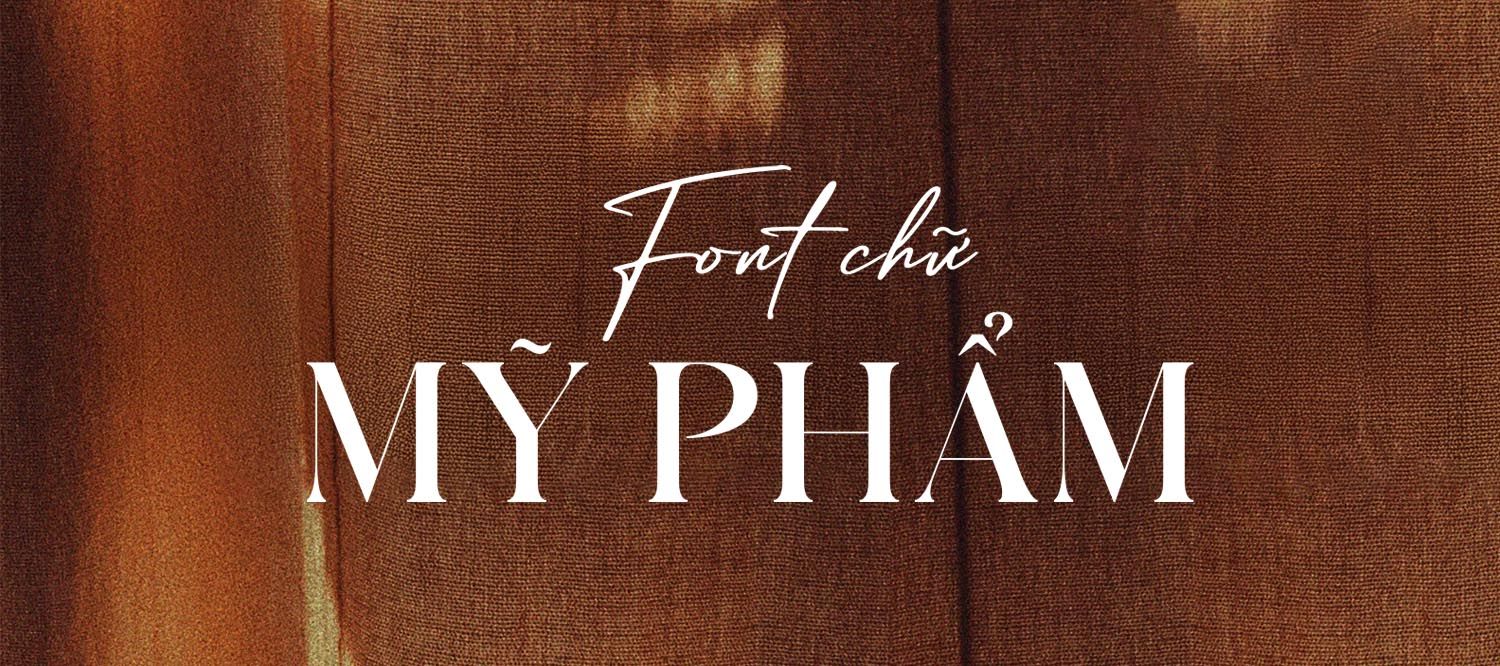
![[Tải Xuống] Tổng Hợp 15+ Font Chữ Mỹ Phẩm Đẹp Cho 2025](https://cdn.s99.vn//cloud/Bt0lgA_font-chu-my-pham-viet-hoa-depjpg.jpeg)
Trong ngành mỹ phẩm, font chữ không chỉ đơn thuần là kiểu chữ để hiển thị thông tin mà còn đóng vai trò là “gương mặt” của thương hiệu. Font chữ mỹ phẩm được hiểu là những kiểu chữ được thiết kế hoặc lựa chọn chuyên biệt để phù hợp với lĩnh vực làm đẹp – thường mang hơi hướng sang trọng, mềm mại và tinh tế. Việc chọn đúng font chữ giúp thương hiệu mỹ phẩm khẳng định phong cách, tạo sự chuyên nghiệp và gây ấn tượng mạnh mẽ với khách hàng ngay từ cái nhìn đầu tiên.
NVN Motherland Signature mang phong cách chữ ký mềm mại, tinh tế với những đường nét uyển chuyển. Font này rất phù hợp cho các thương hiệu mỹ phẩm cao cấp, muốn tạo cảm giác sang trọng và cá nhân hóa. Đặc biệt, nó giúp logo hoặc bao bì trở nên độc đáo, dễ ghi nhớ.
TH Renddonika là font viết tay lãng mạn, kết hợp hoàn hảo giữa sự mềm mại và nữ tính. Font thích hợp sử dụng cho thương hiệu mỹ phẩm, spa, hoặc các dòng sản phẩm thiên về làm đẹp tự nhiên. Nó mang lại cảm giác gần gũi và tinh tế trong từng thiết kế.
TH Bramostia mang phong cách chữ ký uyển chuyển, có độ dày vừa phải và đường cong mềm mại. Font này thường được dùng cho logo hoặc slogan của thương hiệu mỹ phẩm, tạo ấn tượng chuyên nghiệp nhưng vẫn giữ được nét nữ tính.
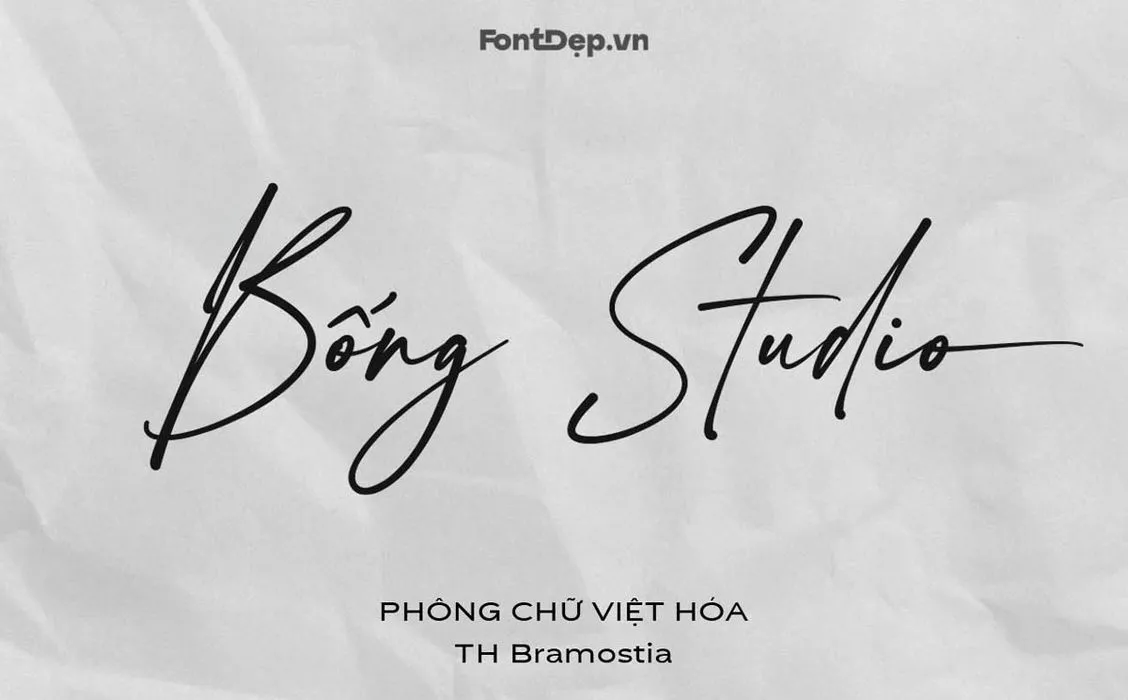
TH Bengoda mang hơi thở hiện đại, nét viết tay cá tính nhưng vẫn tinh tế. Đây là lựa chọn lý tưởng cho các thương hiệu trẻ, năng động trong ngành mỹ phẩm, đặc biệt khi cần thể hiện phong cách cá nhân hóa.
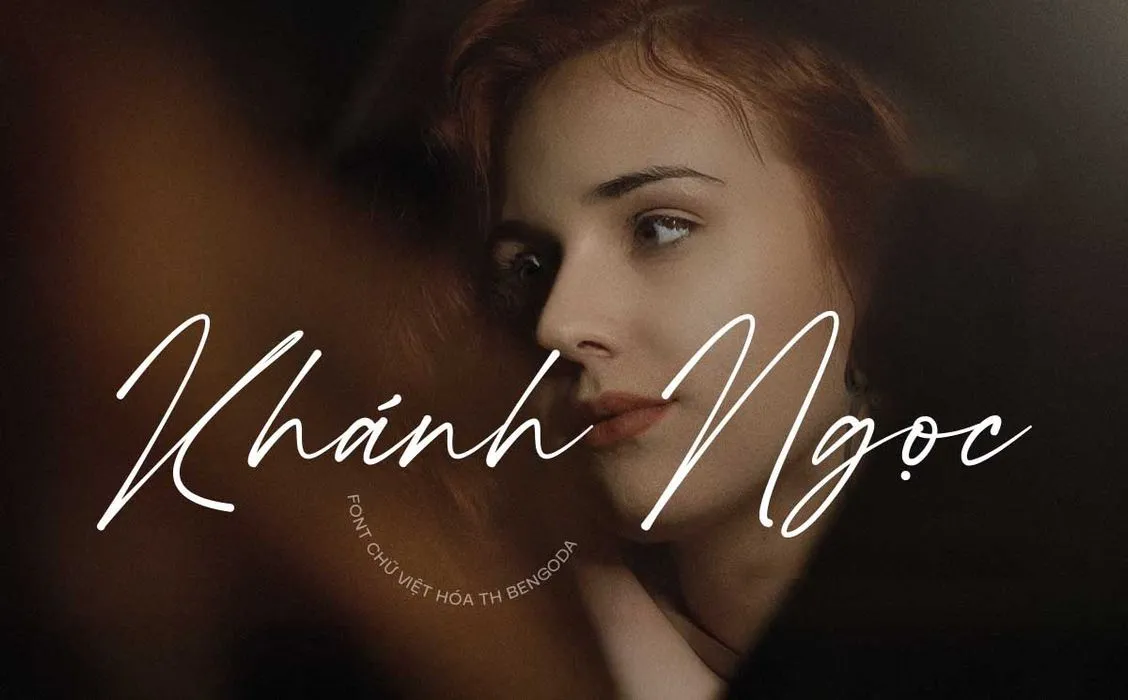
TH Boulderstone là font chữ ký mạnh mẽ, kết hợp giữa sự tinh tế và sự tự tin. Phù hợp cho logo mỹ phẩm muốn thể hiện đẳng cấp, cuốn hút ngay từ ánh nhìn đầu tiên.
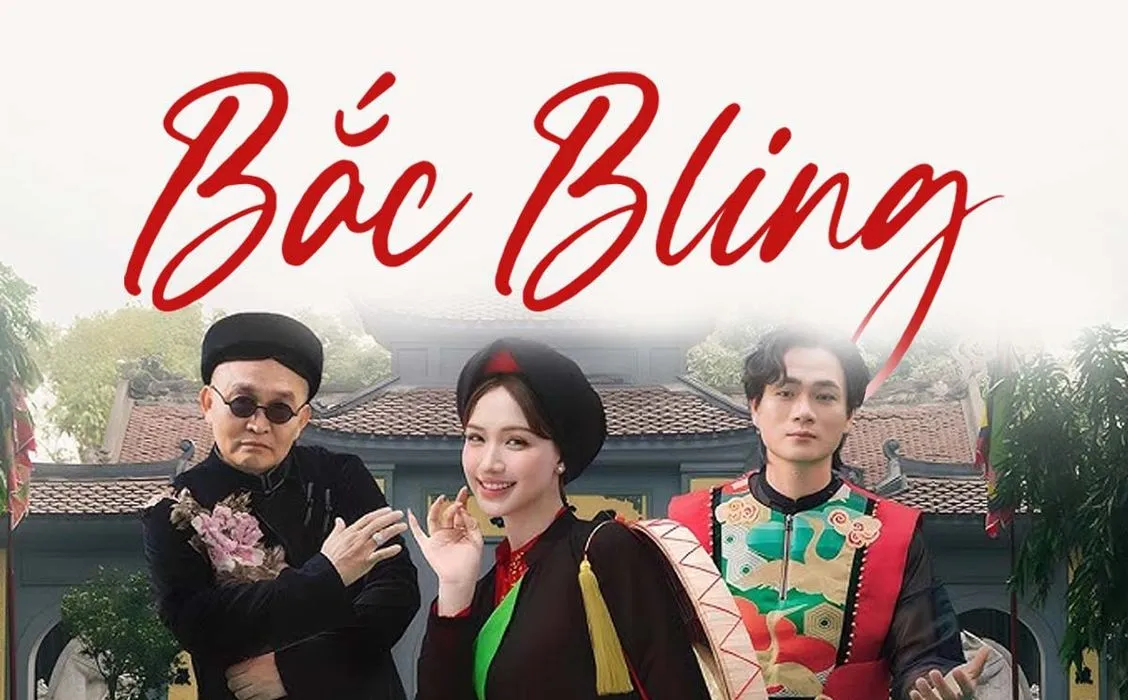
TH Saviera là font sans-serif hiện đại, thanh lịch với đường nét gọn gàng và cân đối. Rất thích hợp cho các thiết kế bao bì, nhãn sản phẩm mỹ phẩm cần sự rõ ràng nhưng không mất đi tính thẩm mỹ.
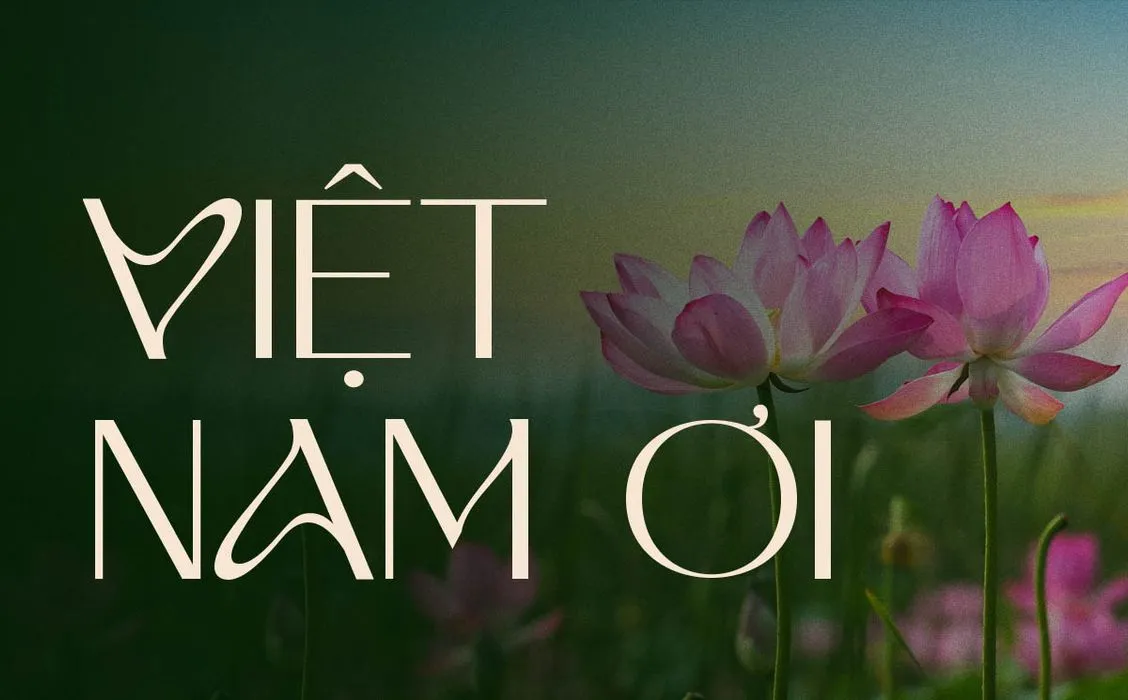
TH Adriana Gabrielle là font chữ viết tay mềm mại, tạo cảm giác sang trọng và tinh tế. Font thường được ứng dụng trong các thiết kế spa và mỹ phẩm thiên về sự thư giãn, nhẹ nhàng.
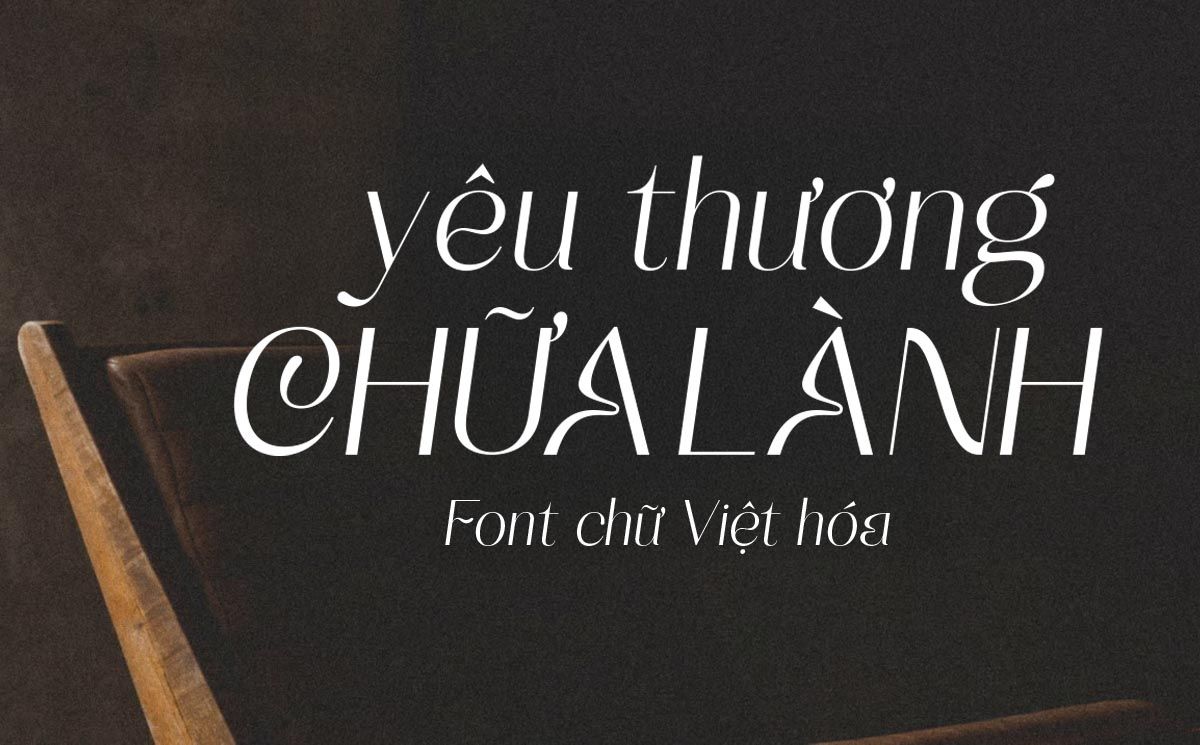
TH Cemains là font sans-serif luxury, mang lại sự hiện đại và sang trọng cho bao bì mỹ phẩm. Font này phù hợp cho các thương hiệu cao cấp, nhấn mạnh sự tinh tế và độ chuyên nghiệp.
TH Grotley mang phong cách sans-serif tinh tế, nhẹ nhàng và hiện đại. Đây là font lý tưởng cho các thiết kế cần sự cân bằng giữa tính thẩm mỹ và tính ứng dụng, đặc biệt là bao bì skincare.
SVN Archattes là một font sans-serif tối giản, miễn phí và dễ dùng. Nhờ sự gọn gàng, font này phù hợp cho các thiết kế website hoặc nhãn mỹ phẩm chú trọng sự rõ ràng và chuyên nghiệp.
TH Luxury là font serif mang phong cách sang trọng, tạo nên dấu ấn cao cấp cho logo hoặc bao bì mỹ phẩm. Nó giúp thương hiệu trở nên chuyên nghiệp và đẳng cấp hơn.
TH Cinema Sunday là font serif thanh lịch, phù hợp cho lĩnh vực làm đẹp và spa. Với các đường nét mềm mại, font này dễ ứng dụng trong poster, tạp chí và bao bì mỹ phẩm.
Tác giả gốc: StringLabs
Việt hóa: TH Team
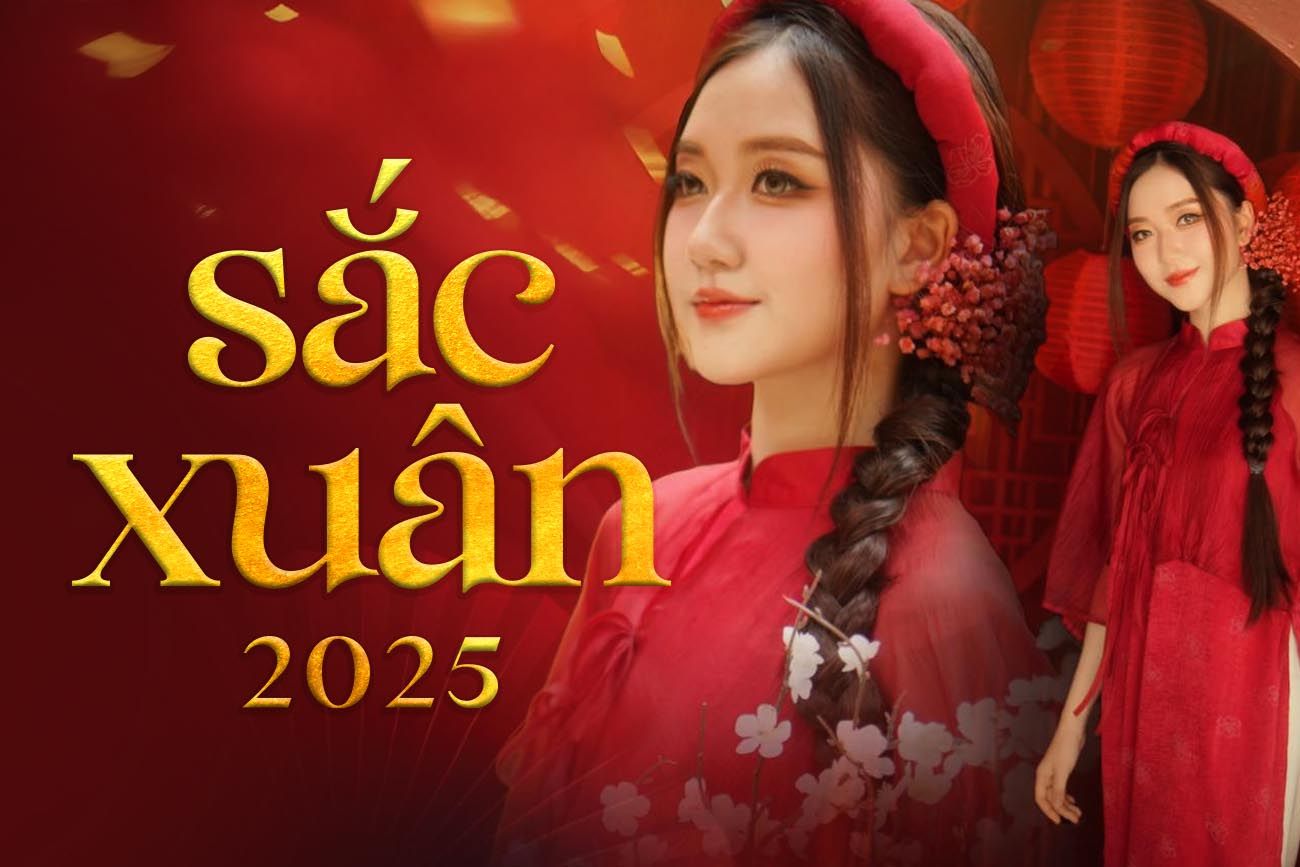
TH Luxury 6 mang phong cách serif hiện đại, sang trọng, được thiết kế để thể hiện sự đẳng cấp. Đây là font lý tưởng cho thương hiệu mỹ phẩm cao cấp, nhấn mạnh sự chuyên nghiệp.
Việt hóa: TH Team
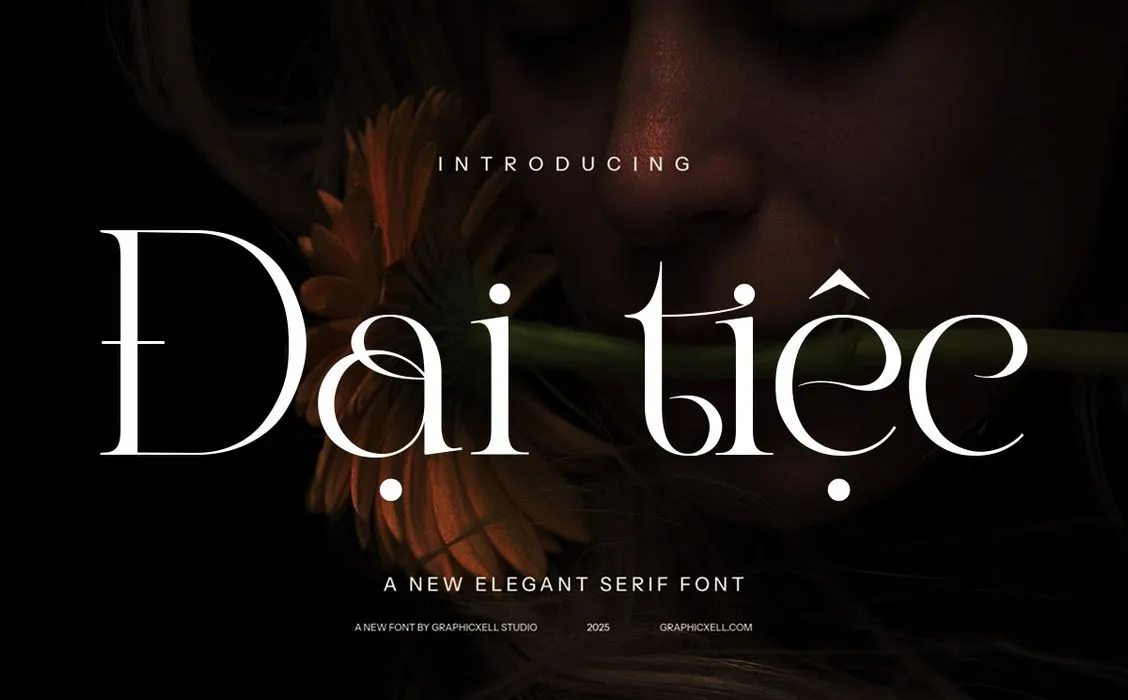
TH Luxury 5 là font serif với các nét mạnh mẽ và rõ ràng, thích hợp cho thương hiệu mỹ phẩm muốn truyền tải sự tin cậy, bền vững và sang trọng.
Việt hóa: TH Team
TH Retalin Regular là font serif miễn phí, được nhiều nhà thiết kế lựa chọn cho bao bì thời trang và mỹ phẩm. Font mang phong cách cổ điển, dễ ứng dụng và đảm bảo tính thẩm mỹ.
Tác giả gốc: Creatype Studio
Việt hóa: TH Team
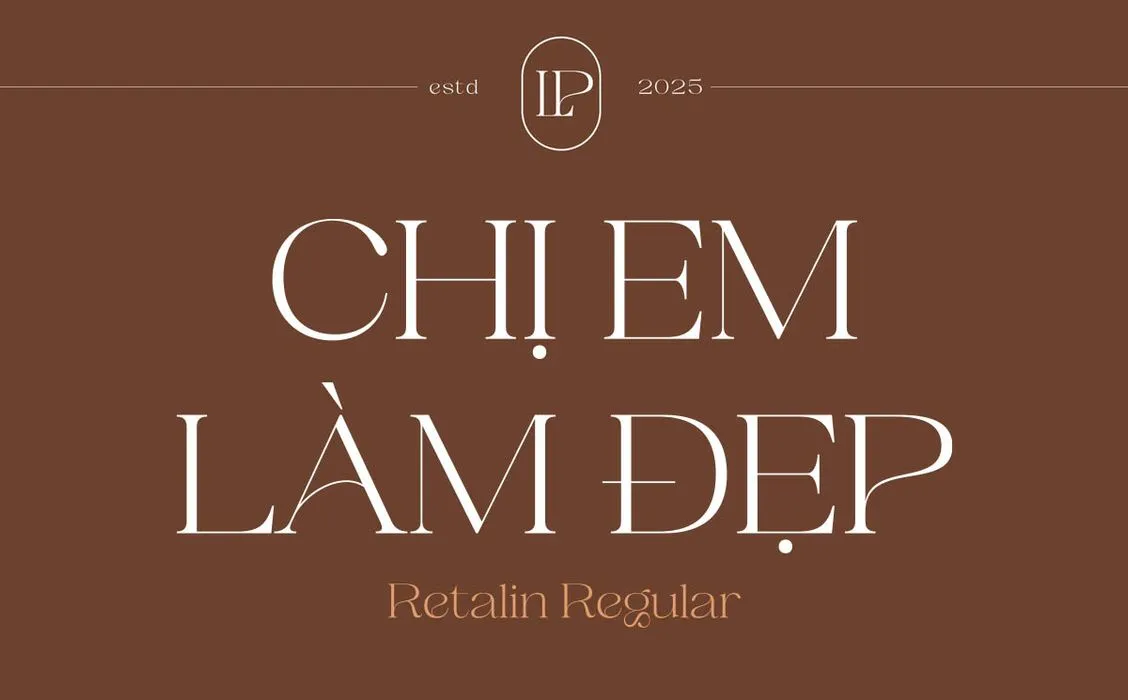
Không sử dụng quá nhiều font trong cùng một thiết kế.
Kết hợp script + serif hoặc sans-serif để tạo điểm nhấn hài hòa.
Ưu tiên tính dễ đọc trên bao bì sản phẩm nhỏ.
Xác định phong cách thương hiệu (sang trọng, trẻ trung, tự nhiên).
Chọn nhóm font phù hợp (script, serif hoặc sans-serif).
Test font trên mockup trước khi áp dụng chính thức.
Lạm dụng font script phức tạp gây khó đọc.
Sử dụng font không đồng nhất trên các kênh truyền thông.
Dùng font không phù hợp với phân khúc khách hàng mục tiêu.